Bạn đã sẵn sàng để cài thêm những bộ font chữ đẹp nhất chưa? Hôm nay, chúng tôi sẽ mang đến cho bạn một lựa chọn tuyệt vời với các phông chữ siêu dễ thương trong top Font chữ sang trọng việt hóa, hiện đại nhất dưới đây.
Hiện nay, việc sở hữu những font chữ đẹp luôn là mong muốn thiết thực của nhiều user, không hẳn chỉ là dành riêng cho các nhà thiết kế đồ họa. Cài và dùng những font chữ sang trọng việt hóa, hiện đại sẽ giúp chúng ta, giúp user có được những chữ đẹp, ấn tượng, có được những bức ảnh sinh động, những logo độc đáo, hay là những banner tuyệt đẹp, lôi cuốn…
Những font chữ hiện đại, sang trọng việt hóa đẹp nhất
Vì những lý do ở trên, Bảo Tiến Giang đã sưu tầm, tuyển chọn và dành riêng bài viết này để gửi đến bạn đọc những mẫu font chữ đẹp, sang trọng việt hóa, hiện đại nhất để các bạn lắp đặt, dùng phục vụ cho công việc của mình. Còn bây giờ, hãy cùng chúng tôi khám phá ngay các mẫu font chữ hiện đại, sang trọng này nhé!
Top Font chữ sang trọng việt hóa, hiện đại
1. Ảnh minh họa một số font chữ sang trọng, hiện đại
Hình dưới là mẫu font chữ BillionStars.
Còn đây là mẫu font chữ hiện đại Allorta.
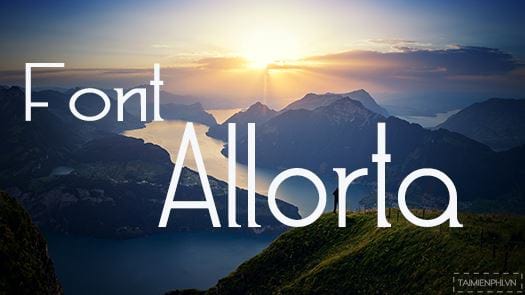
Tiếp theo là mẫu font chữ sang trọng Decotech.
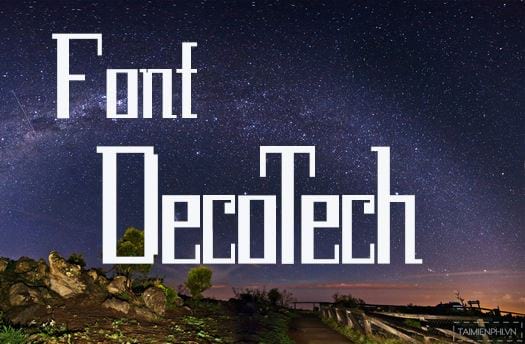
Font Bravada-arma tuyệt đẹp, hiện đại.
Mẫu font chữ Pateglamt Script đẹp, với những nét viết mềm mại.
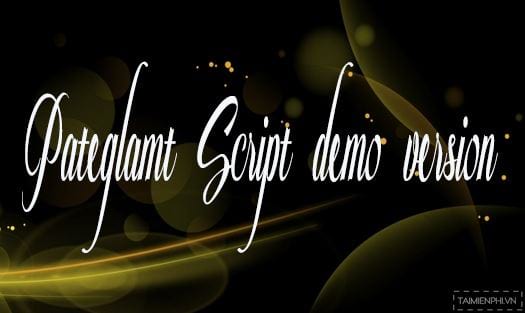
Font Valkyrie sang trọng mang phong cách cổ điển.
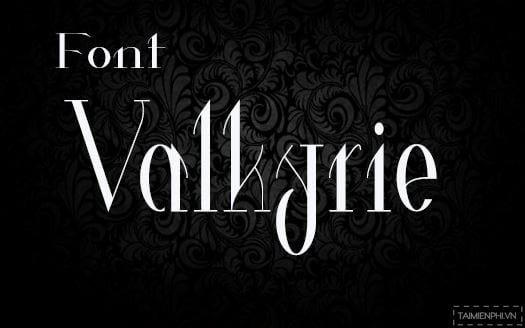
Mẫu font Vonique-64 lịch lãm, sang trọng và đẹp mắt.
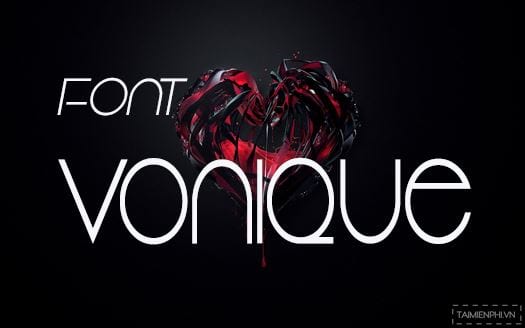
Thêm một mẫu Pateglamt Script đẹp, hiện đại, sang trọng.
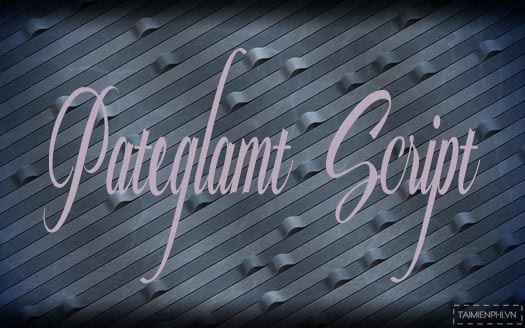
Còn đây là mẫu font Respective uốn lượn nhưng không kém phần đẹp mắt.